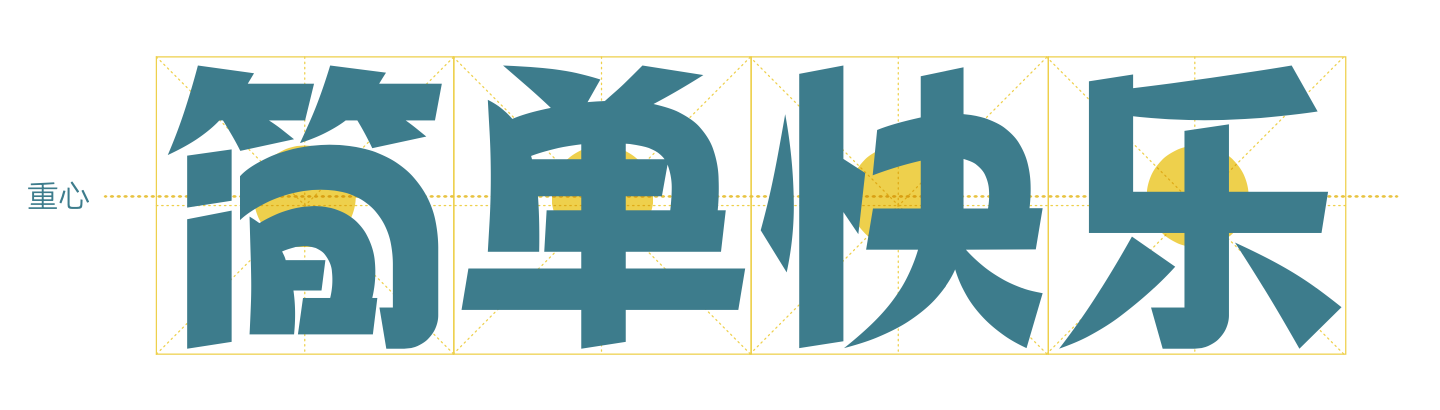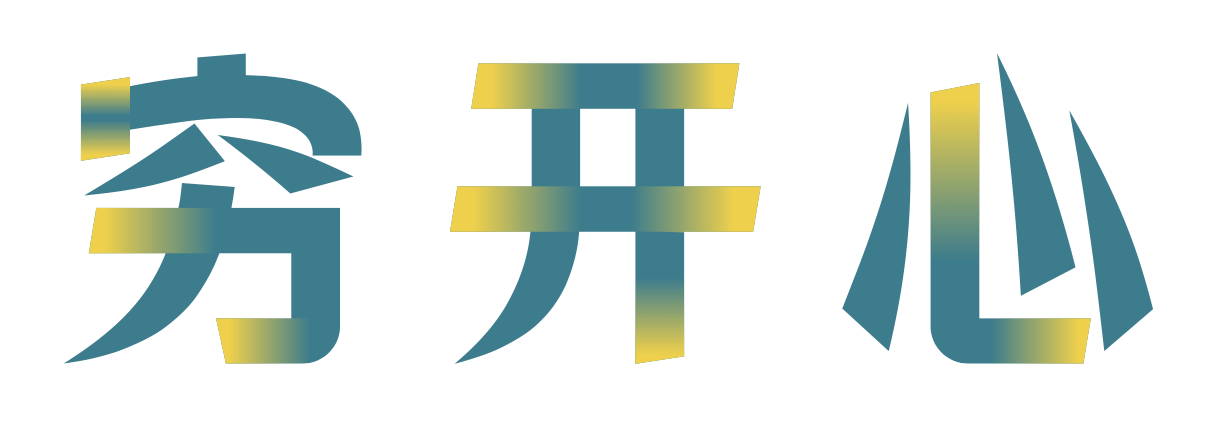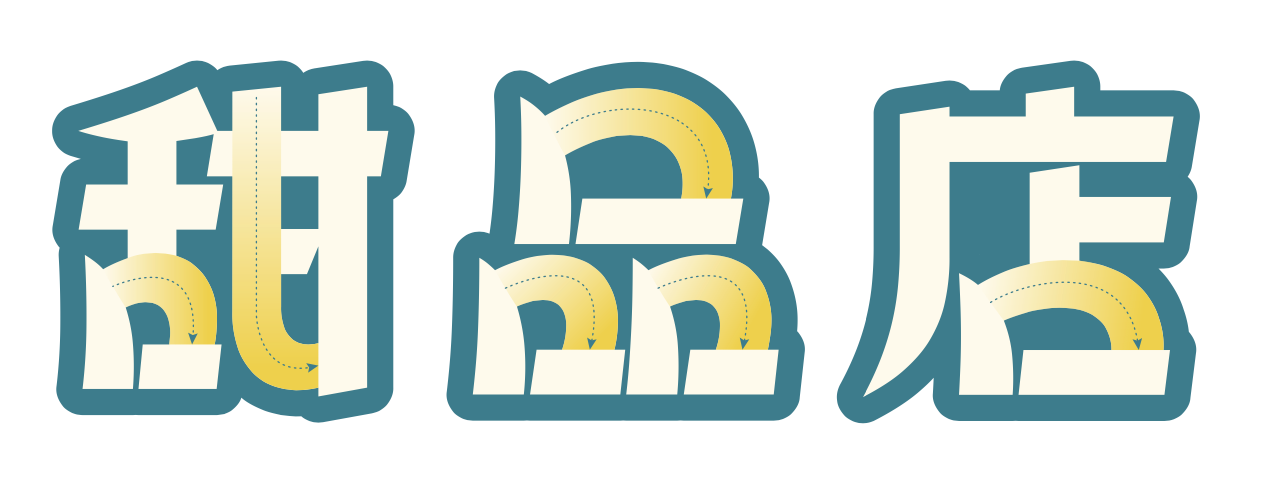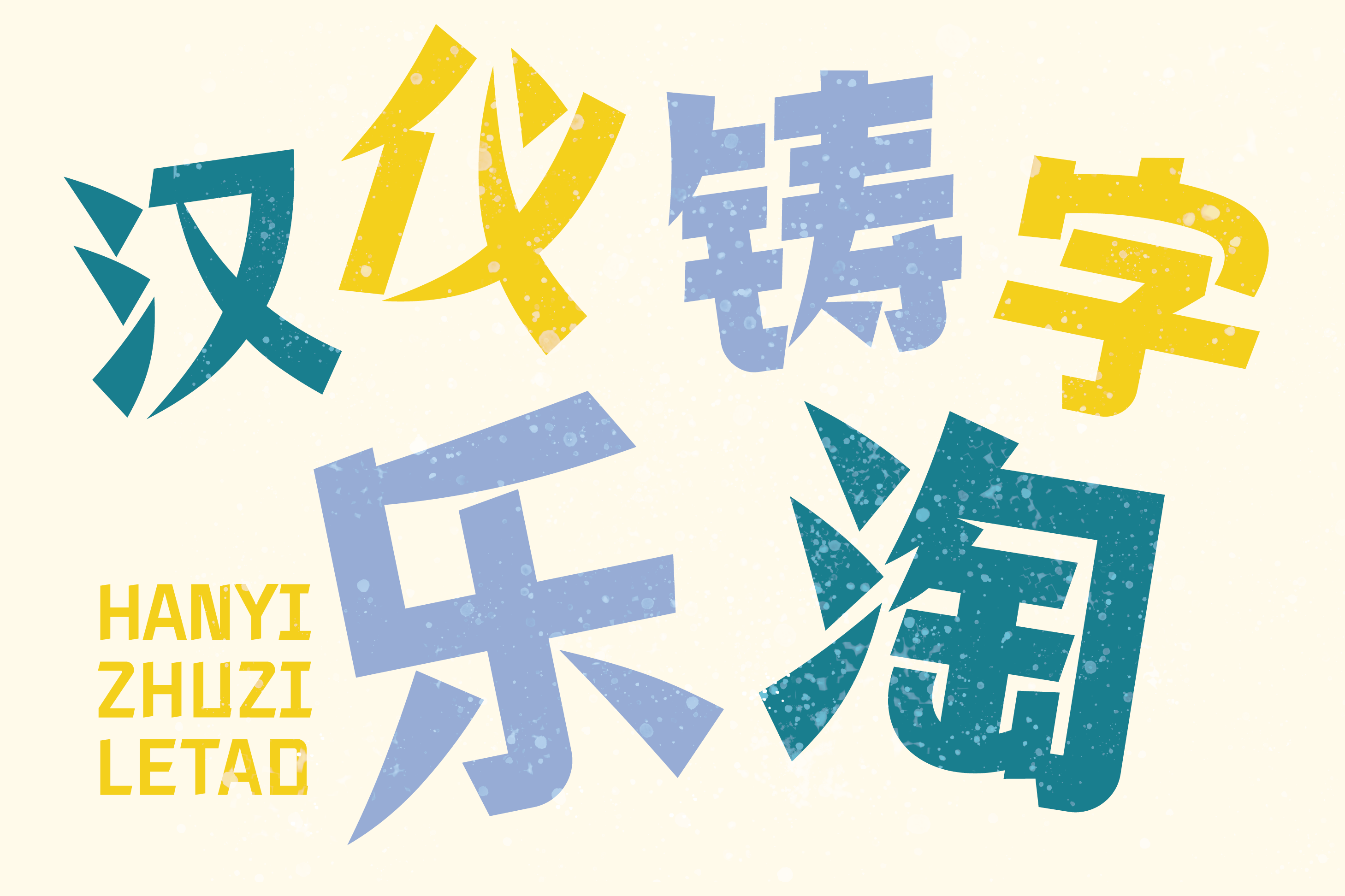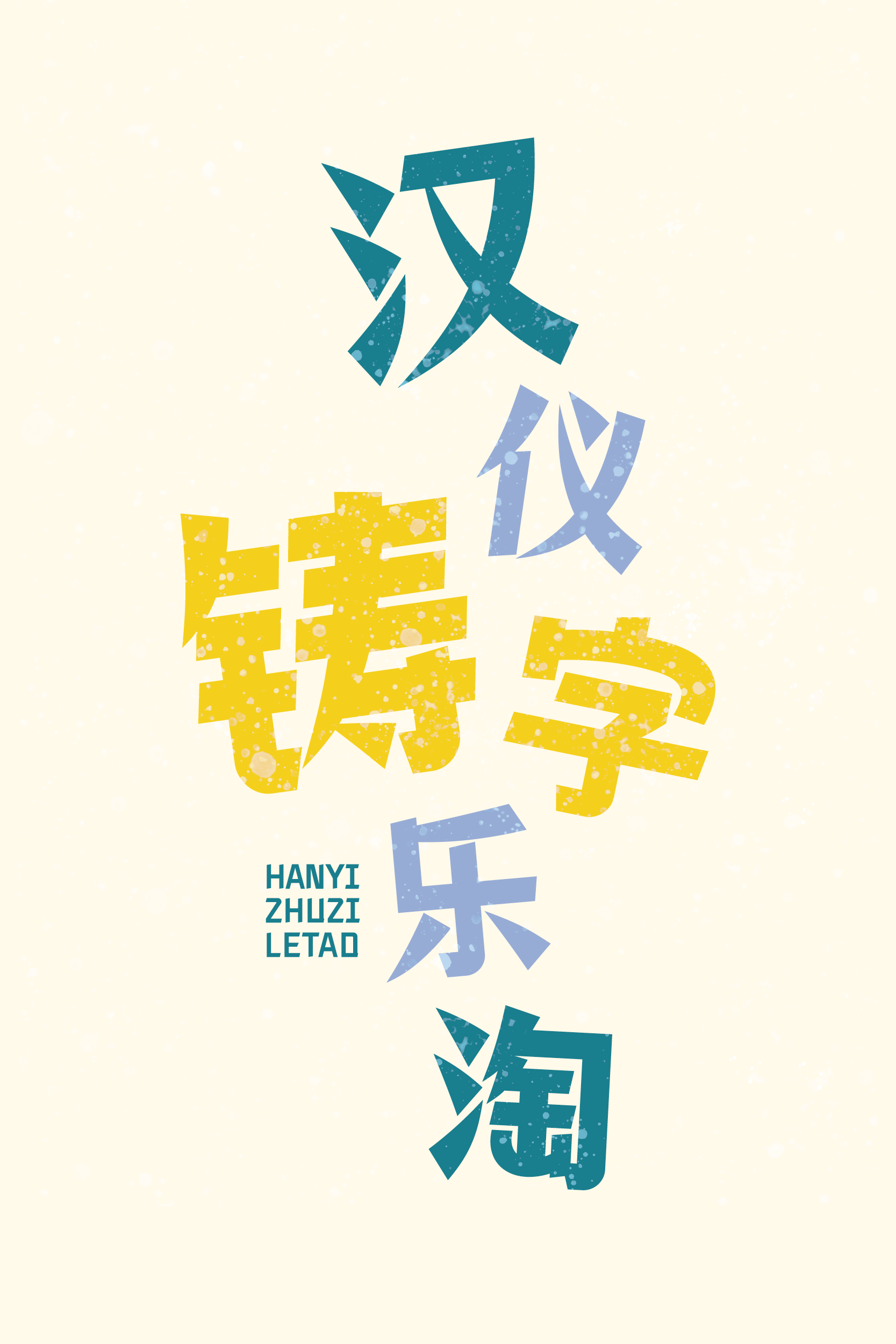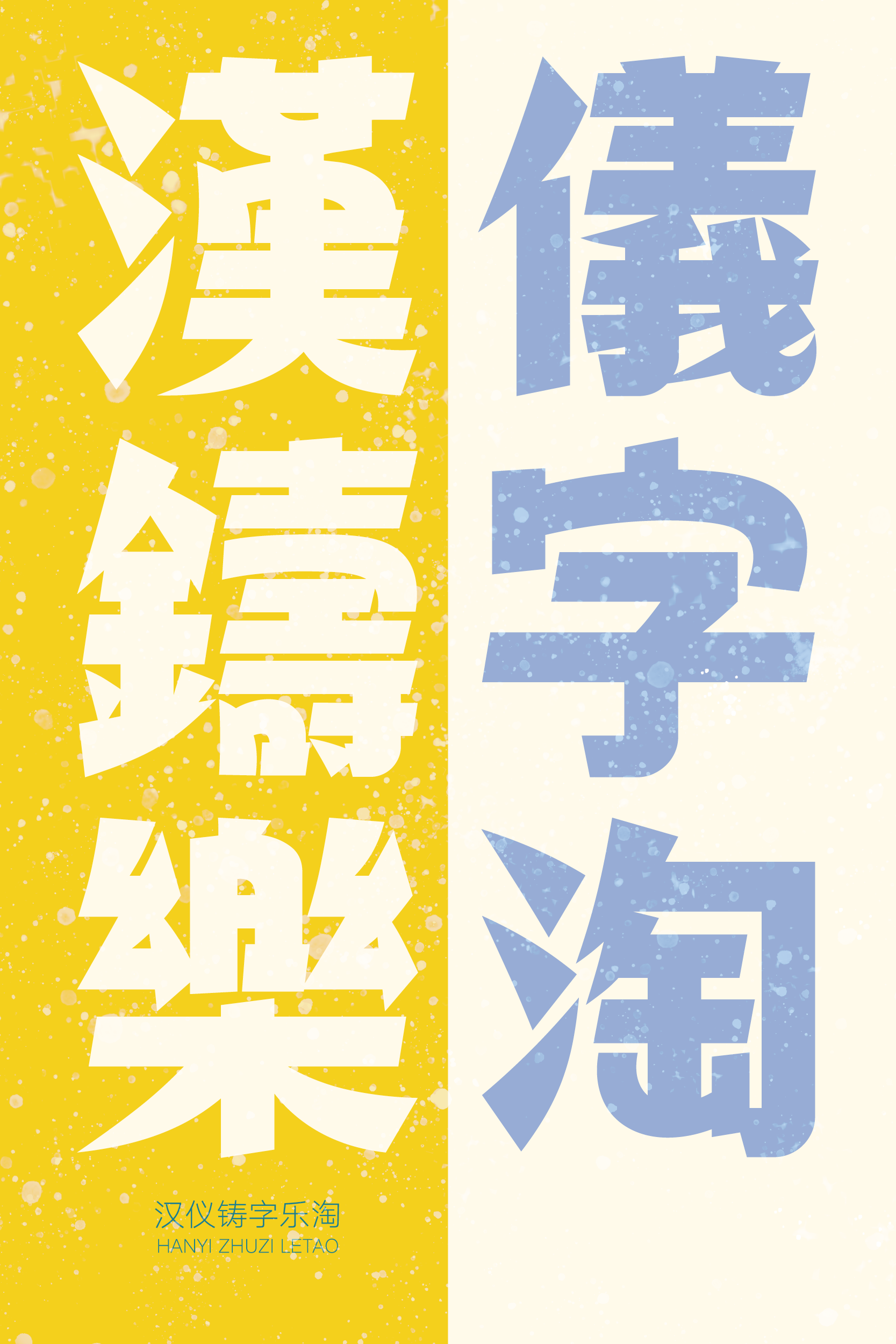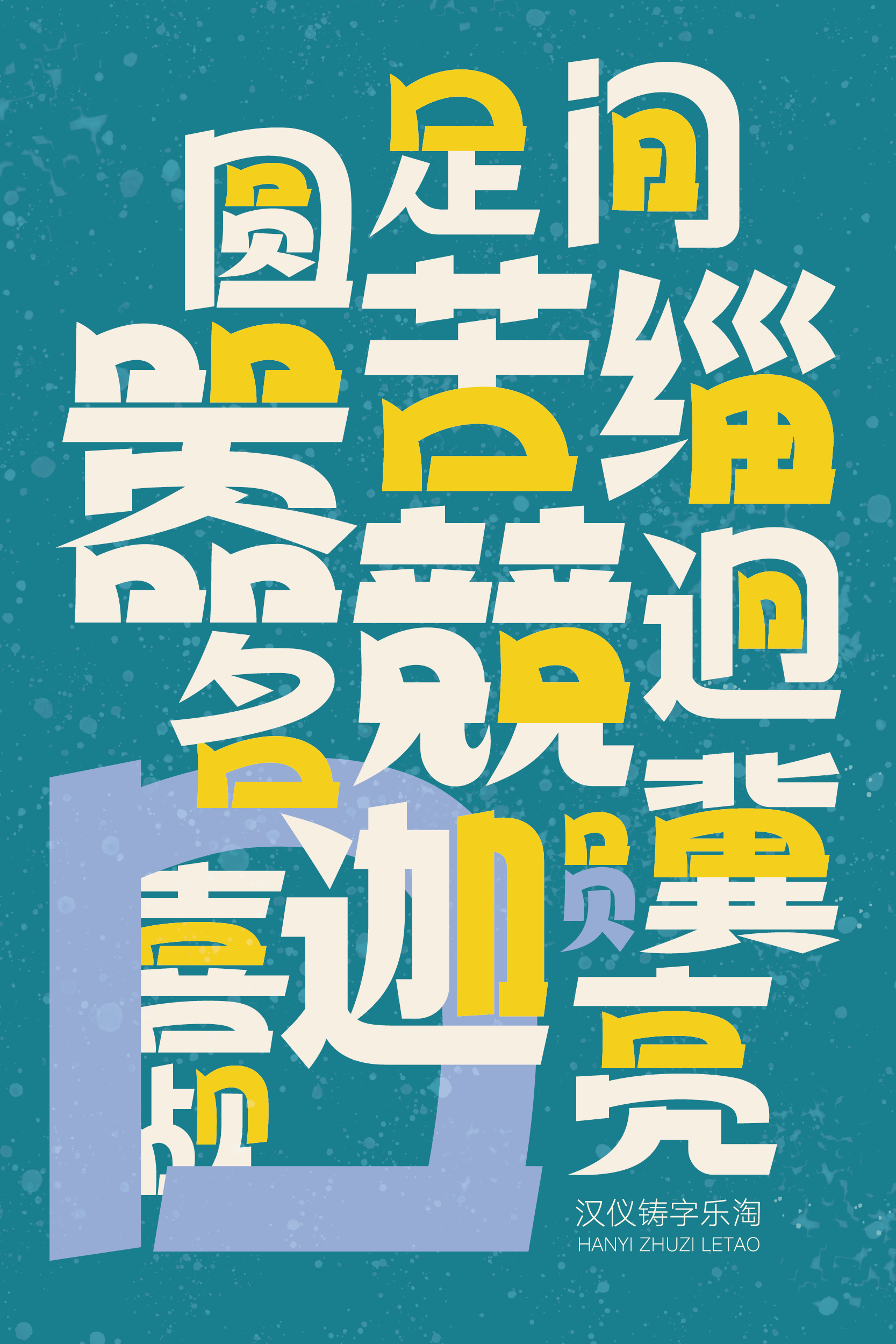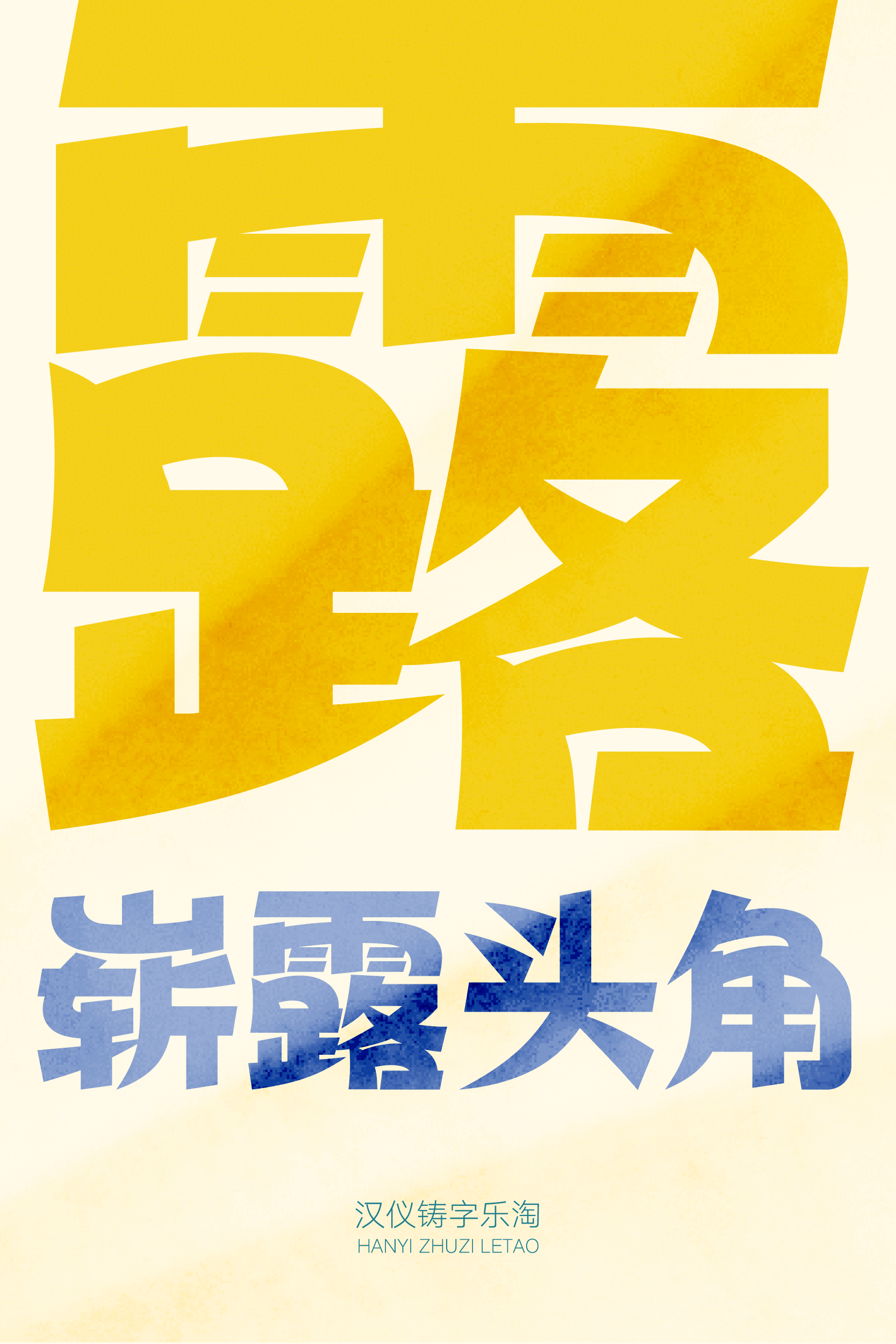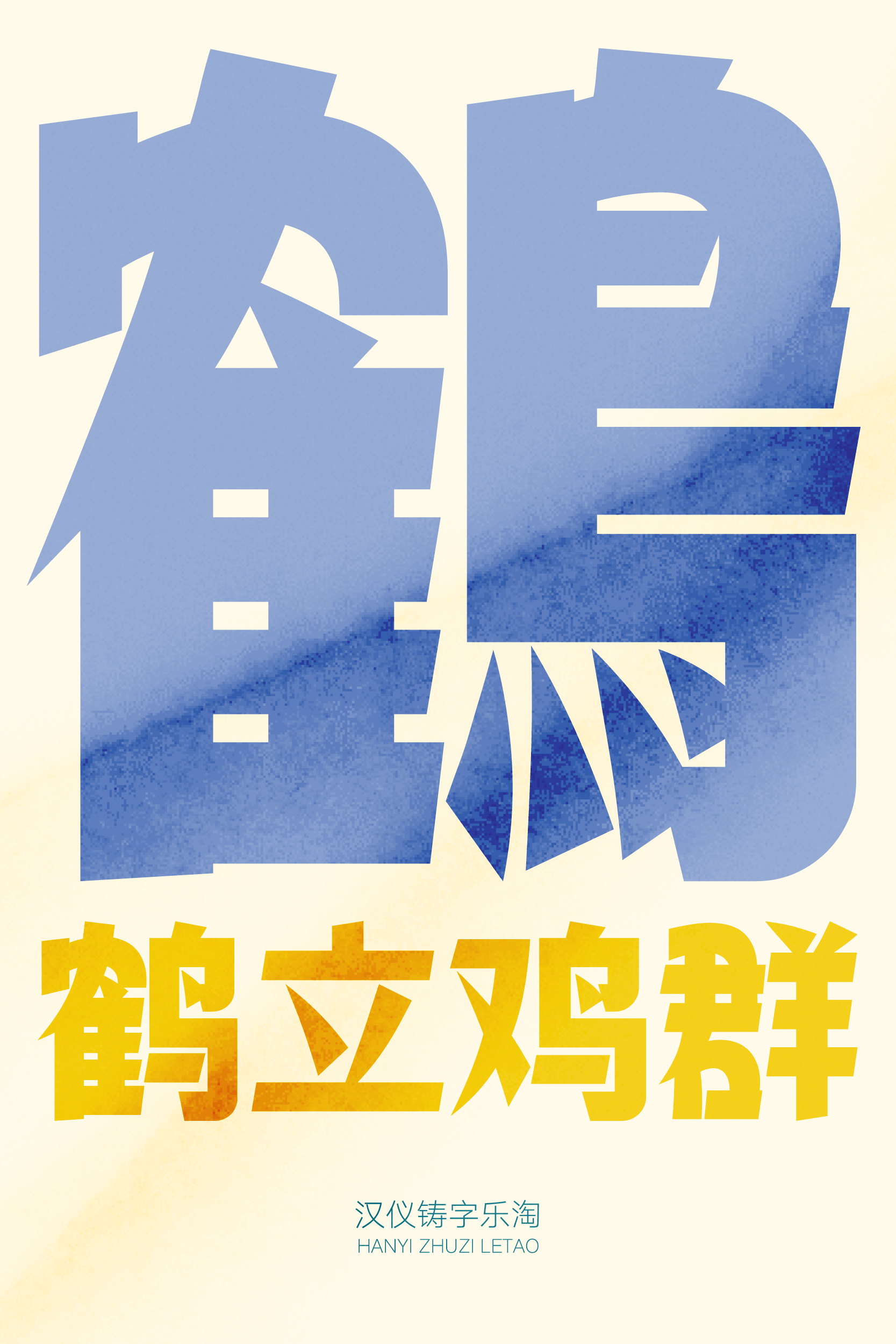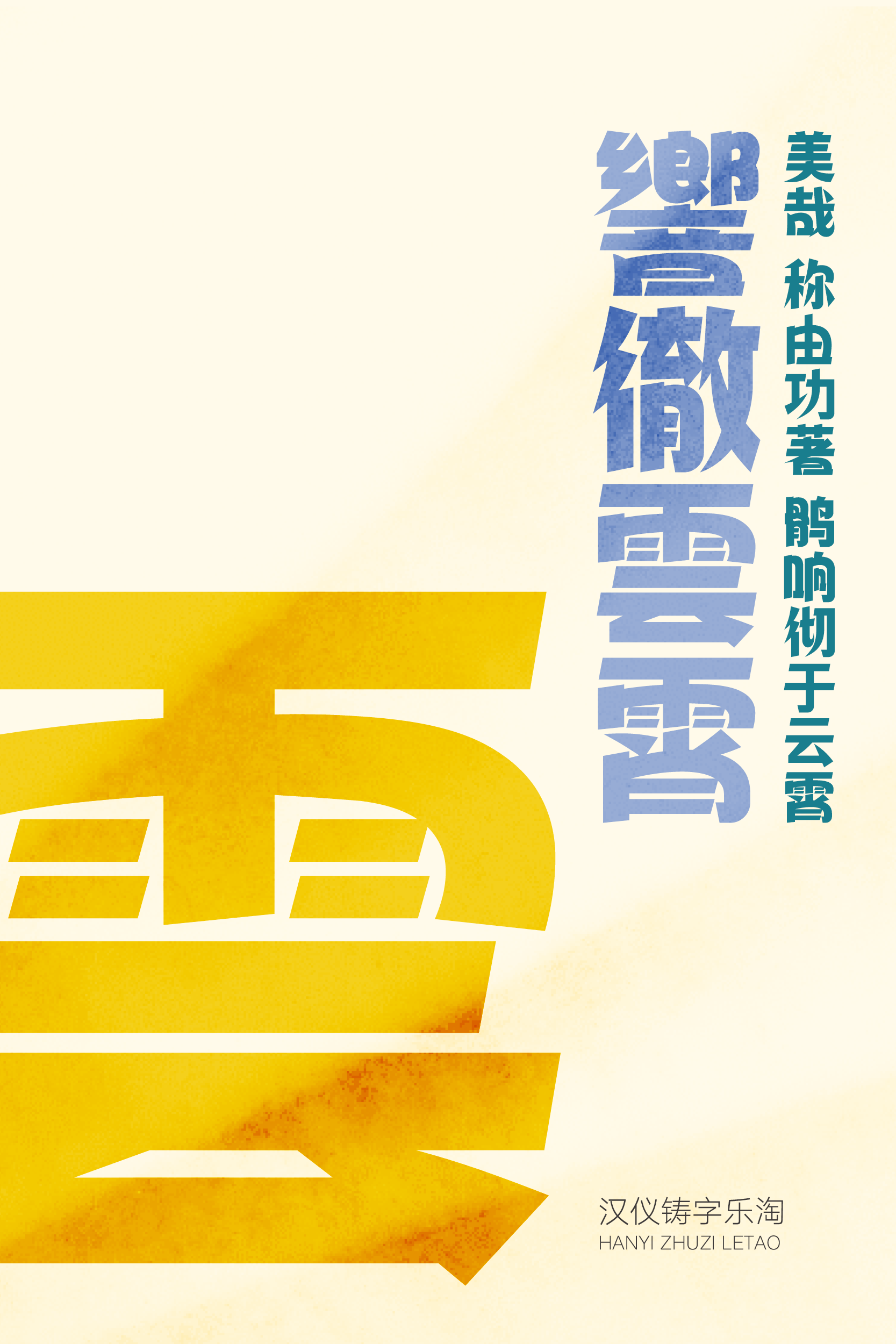
汉仪铸字乐淘字体介绍,汉仪铸字乐淘设计灵感
现代 / 休闲 / 活泼 / 有趣 / 卡通
品牌广告 / 游戏动漫 / 产品包装 / 娱乐综艺 / 书籍封面 /标志LOGO
汉仪铸字乐淘 | 整体特点
“汉仪铸字乐淘”是汉仪旗下的“铸字社工作室”打造的一款美术标题字。这款字有着欢乐、动感的风格特点,适合在轻松、娱乐、年轻化的设计场景中使用。
汉仪铸字乐淘 | 字形特点
“汉仪铸字乐淘”的重心略微偏上、结构空间均衡、字面趋于方形。在标题字的排版使用中,可使版面达到整齐干净而又吸引人眼球的视觉效果。
汉仪铸字乐淘 | 笔画特点
“汉仪铸字乐淘”的笔画横平竖直,横画与竖画的首尾两端以统一的斜切角呈现,干净利落,简洁硬朗。
“汉仪铸字乐淘”的折笔画用饱满的弧形来表现,流畅的线条使字形更加温和柔美、轻松华丽。
“汉仪铸字乐淘”的笔画有直有曲、棱中有圆、润中有方、刚柔并济,呈现出了工整俏皮、美观大方、轻松活泼的字体面貌。
汉仪铸字乐淘 | 中西文匹配
“汉仪铸字乐淘”的西文字母有着和中文一样的笔画特点,中西文搭配使用十分和谐。
汉仪铸字乐淘 | 排版效果